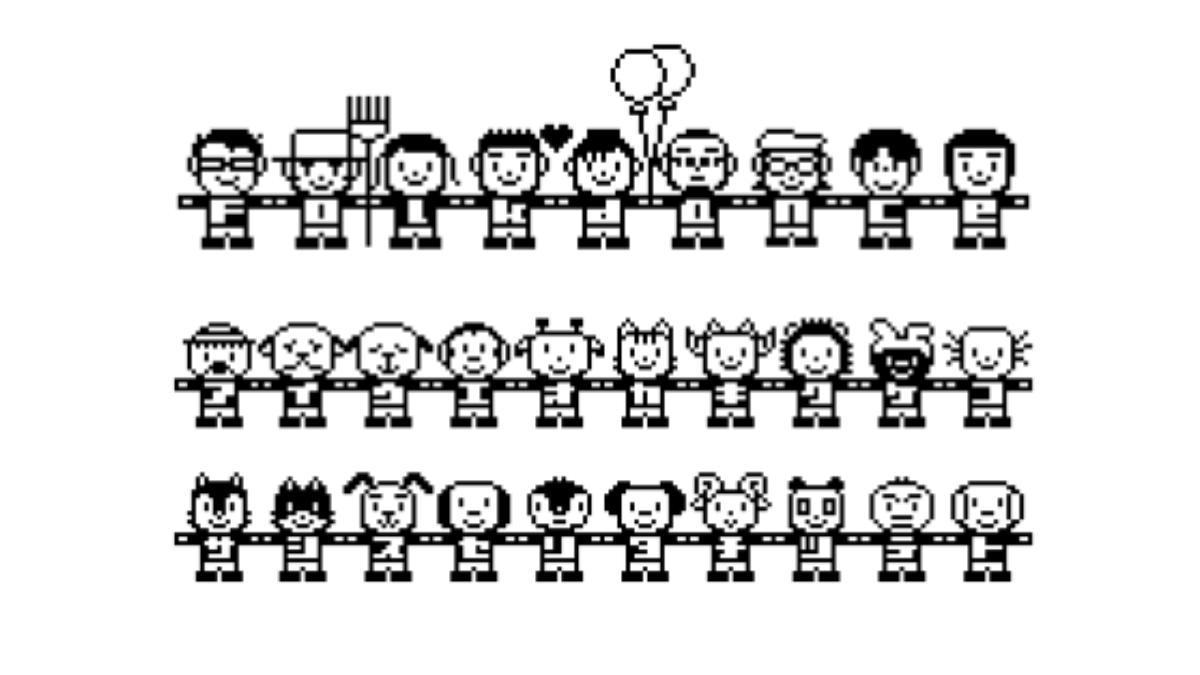
フォークダンス ANIMALは、かわいらしいデザインの25ptの動物が手を繋いだビットマップのカタカナフリーフォントです。1バイト入力のため入力支援ソフトがあると便利です。
フォークダンス ANIMALの詳細情報
| 書体名 | FolkDanceAniamla |
| 書体 | ビットマップ |
| 収録文字 | カタカナ |
| 提供元 | フロップデザイン |